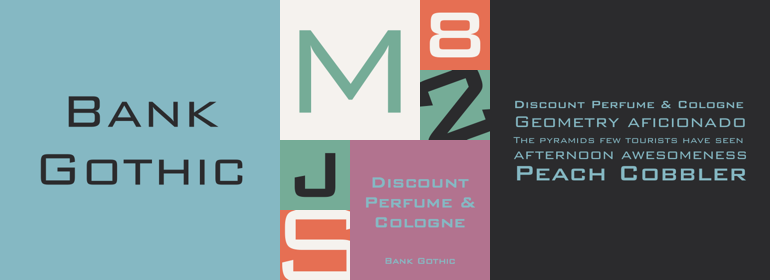
Bank Gothic
Bank Gothic,这款字体结构工整、笔画清晰,兼顾美观与易读性,适用于标题、正文、海报、包装、LOGO 等多种场景。字形优雅稳定,风格百搭耐看,适配日常排版与创意设计,让文字呈现更舒适、更具质感。Bank Gothic一笔一画,皆是细节,以均衡的比例、流畅的线条打造舒适视觉体验,字形端正大气,风格简约现代。无论是商业设计、品牌宣传还是日常排版,都能轻松驾驭,让文字更有格调与力量。Bank Gothic字体下载。
字体品牌: Bitstream(Monotype) 设计师:Benton,Morris Fuller 字体分类:无衬线体 字体属性:外文 字符集:Unicode 发布时间: 2018